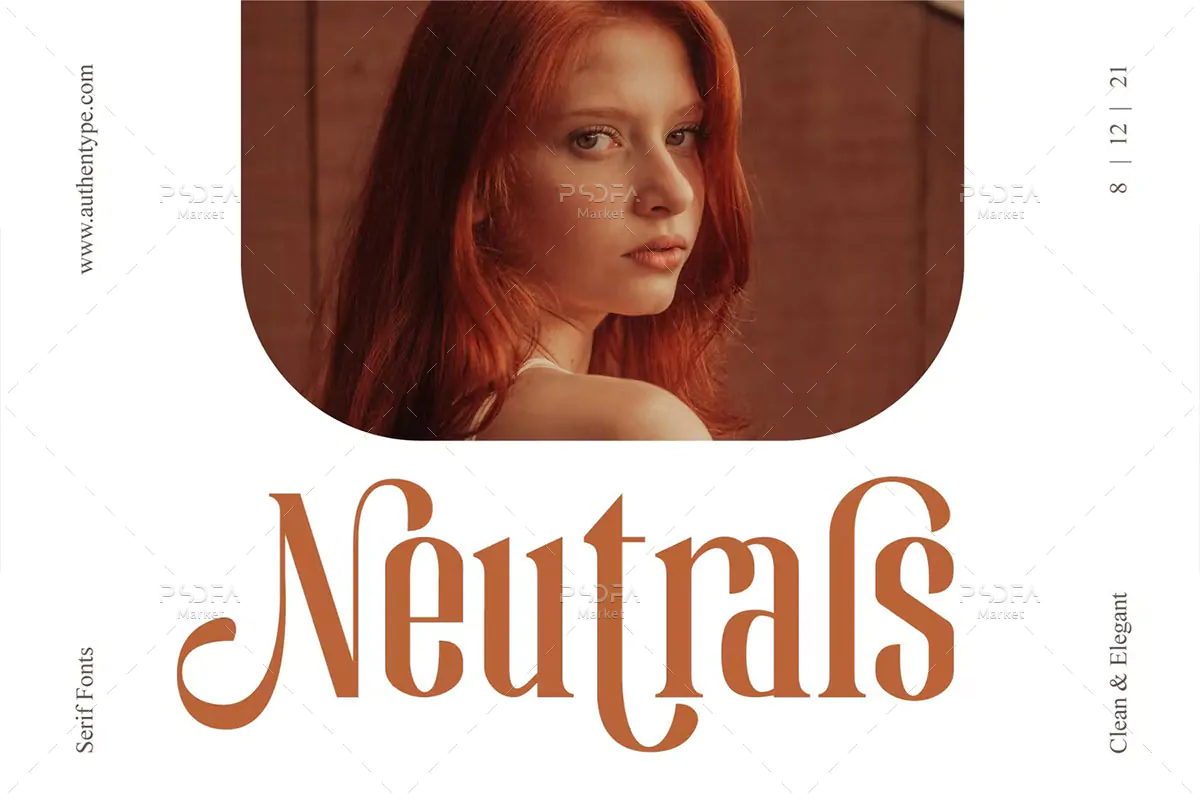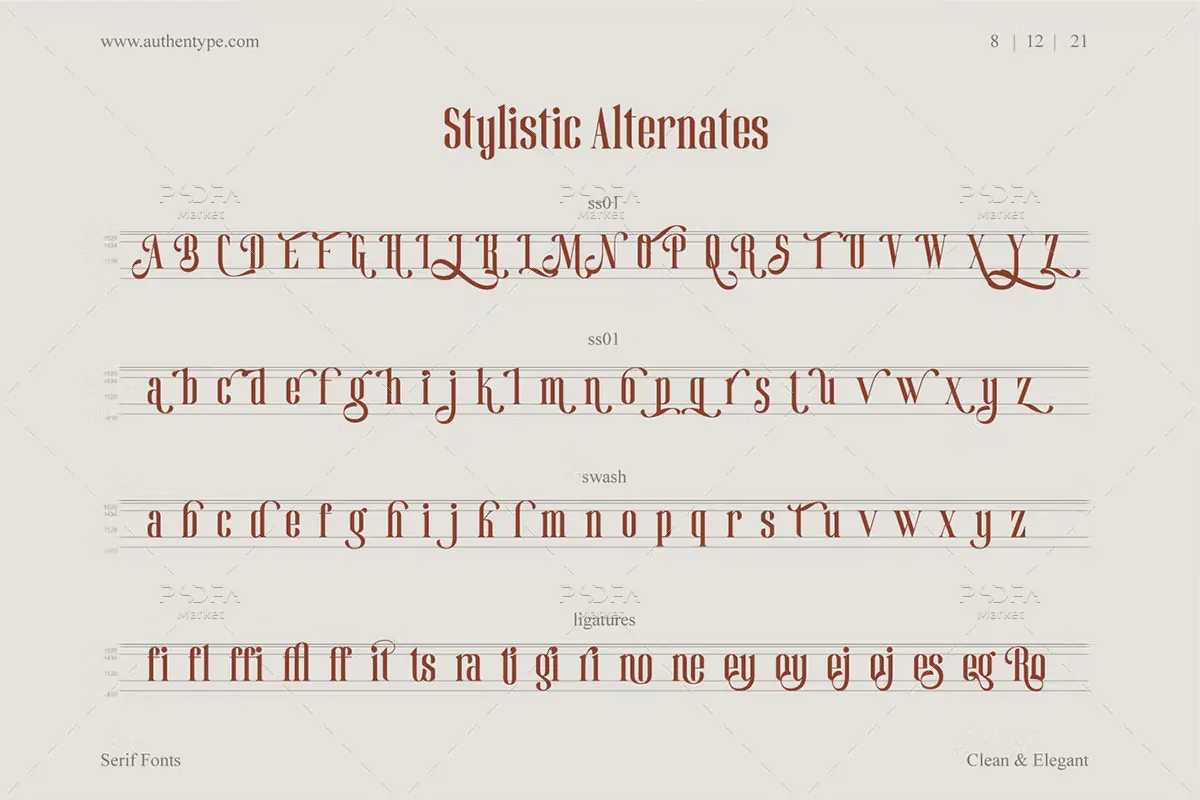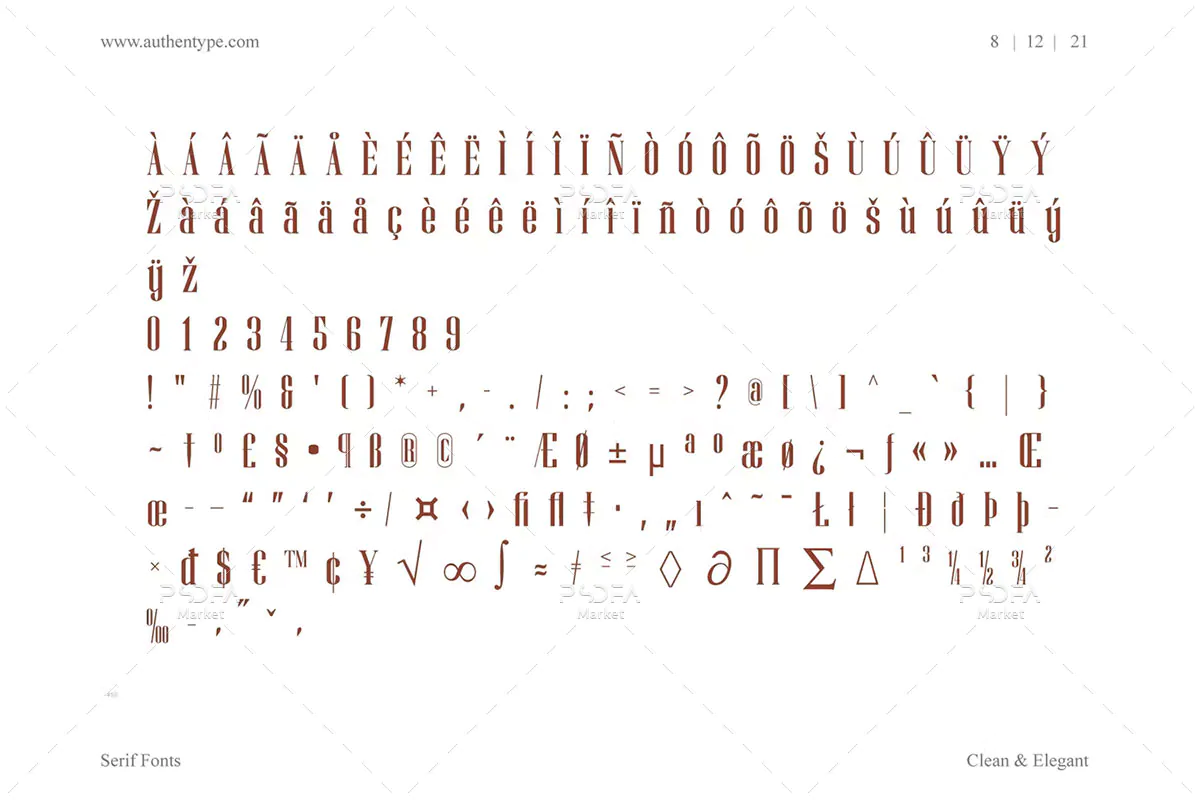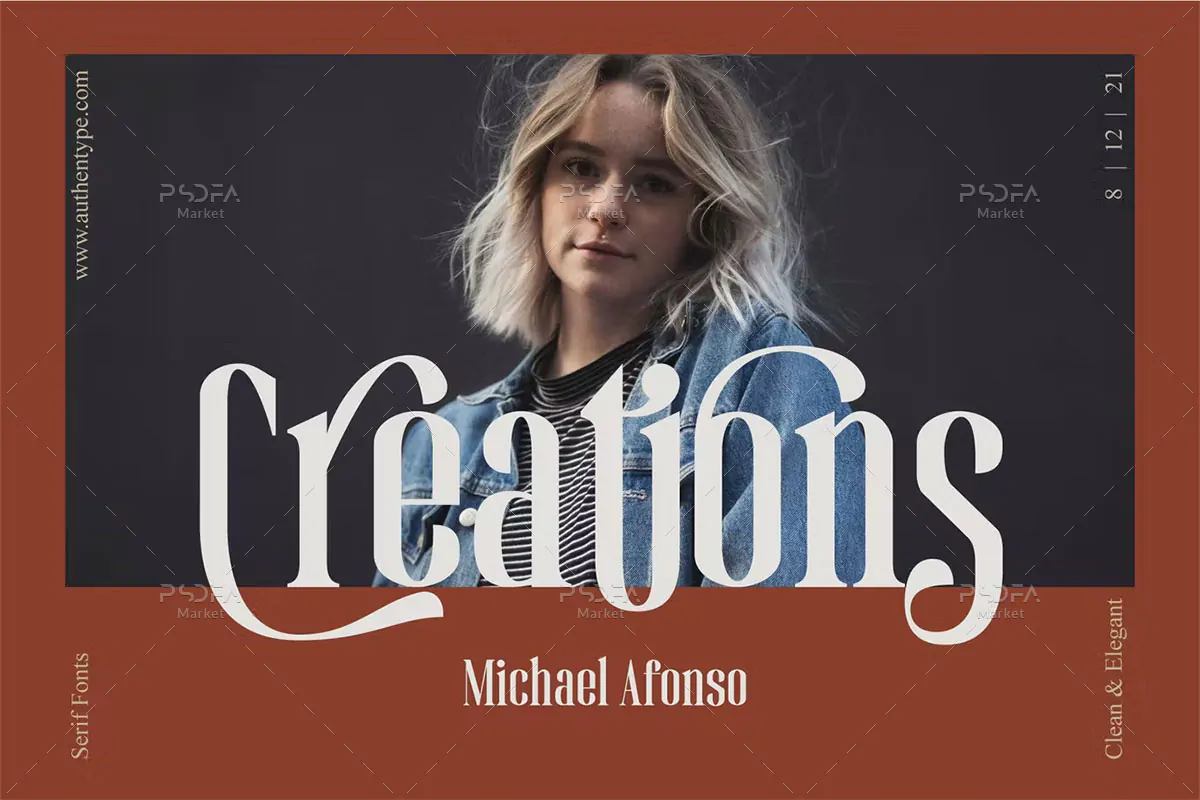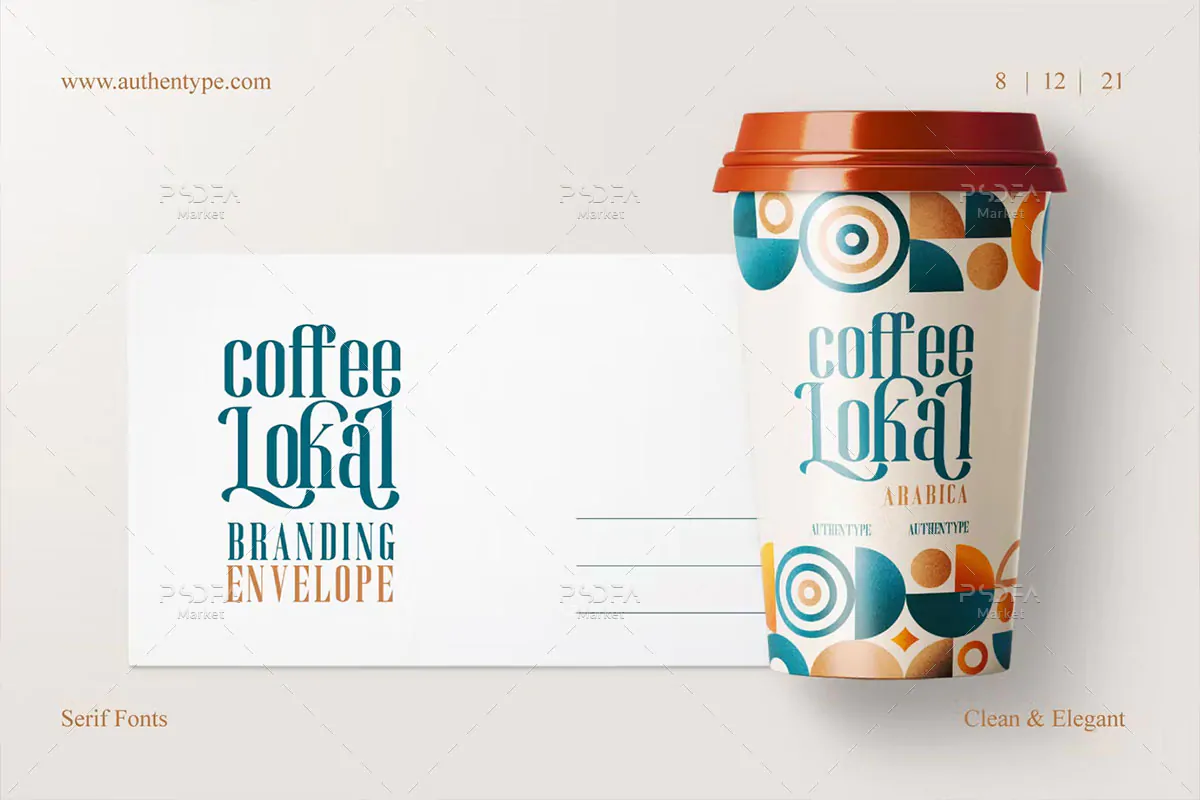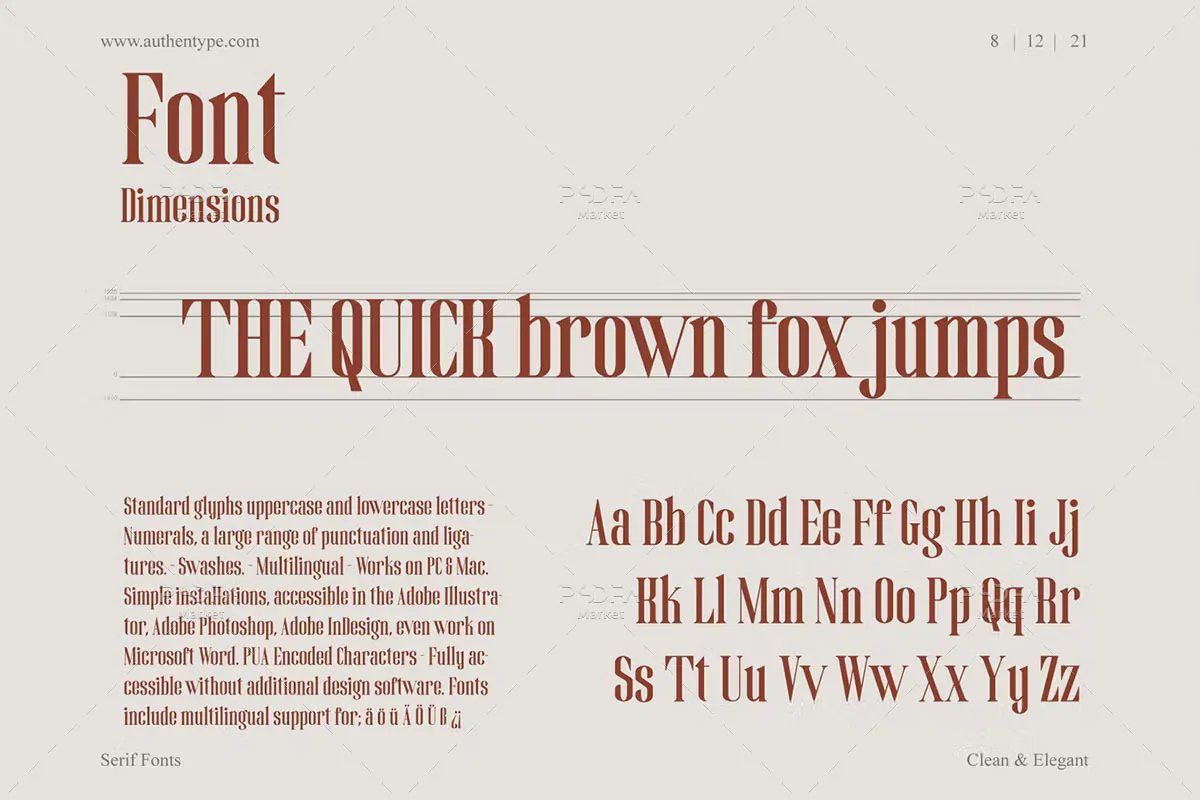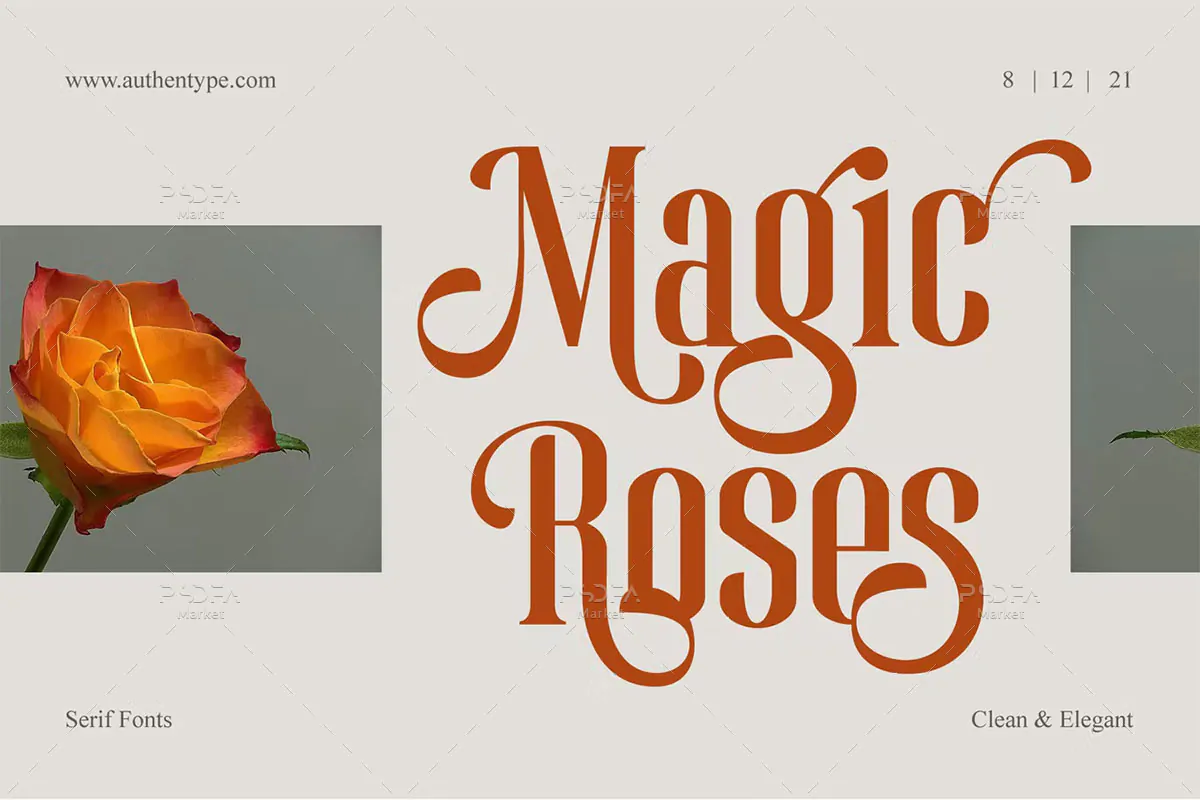
فونت شیک و ظریف Magic Roses
فونت شیک و ظریف انگلیسی
فونت شیک و ظریف Magic Roses یک قلم سریف فوق العاده زیبای انگلیسی است که با اشکال مختلف طراحی شده است و مناسب جهت استفاده در طرح و پروژههای گرافیکی مختلف میباشد. فونت Magic Roses با وزن معمولی طراحی شده است که میتوانید از آن در طراحی کارت پستال، کارت دعوت، ظروف یکبار مصرف، بسته بندی محصولات، لوازم التحریر و … استفاده کنید.